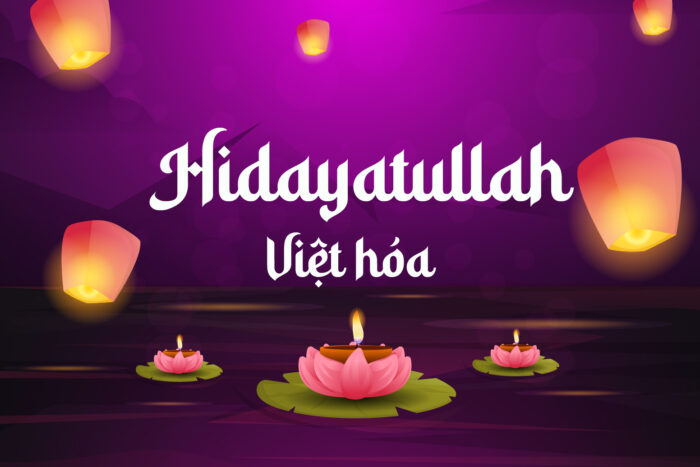
KD Hidayatullah Việt hóa – Font chữ phong cách Ấn Độ, Phật giáo
KD Hidayatullah Việt hóa là một phông chữ độc đáo mang đậm phong cách Ấn Độ và Phật giáo. Với thiết kế tinh xảo, các đường nét mềm mại và uyển chuyển, phông chữ này gợi nhớ đến nghệ thuật thư pháp cổ điển. Các ký tự của KD Hidayatullah được thiết kế với những chi tiết tỉ mỉ, tạo ra sự kết hợp hoàn hảo giữa tính truyền thống và hiện đại. Đặc biệt, phông chữ có thể được ứng dụng trong các thiết kế liên quan đến văn hóa, tôn giáo, và nghệ thuật, như bìa sách, tiêu đề bài viết, và các ấn phẩm quảng cáo. Sự kết hợp giữa phong cách thư pháp Ấn Độ và các yếu tố Phật giáo mang lại một cảm giác trang trọng và linh thiêng, phù hợp cho các sự kiện lễ hội và tôn giáo. Với sự Việt hóa, KD Hidayatullah trở nên dễ dàng tiếp cận và sử dụng hơn cho người Việt, góp phần làm phong phú thêm kho tàng văn hóa đồ họa.